大家可能在网上看过很多关于矢量图标制作的教程,而且大多是技术同学分享的技术贴。整个过程也相对比较简单。在这里我们将深入地向大家讲述字体图标制作的规范流程和注意事项,很多内容是现在网上没有的,纯粹是阿里妈妈MUX这两年摸索出来的。阿里妈妈MUX在国内首家推出了在线生成字体图标平台,省去了设计师不太擅长的字体制作过程,所以在本教程中我们就不再详细介绍如何使用字体制作工具制作字体图标的过程,更多的是介绍如何在AI工具中制作一个规范的字体图标。
一、制作前基础知识普及
2、尽量使用illustrator制作矢量图标;有些设计师在ps中使用路径绘制图标再导成SVG,这种方式也是可以的,但是有时会出现一些奇怪的现象,如图形的路径混乱了,图标倾斜了等不可预知的情况,所以还是建议大家在illustrator中绘制矢量图标;
4、在绘制图标的过程中不要使用AI图形模块的旋转、镜像等功能,整个绘制过程最好使用钢笔工具绘制;^^
5、避免出现图形绘制过中断点的现象。
6、不可以用色彩叠加的方式来达到模块造型;
二、图标栅格
数字形态下,字符是用抽象化的图案绘制成的。当文本显示在屏幕上时,位置非常精确,理想的字体形状需要用一定数量的像素栅格显示。图标设计师常用栅格来控制图标组成元素的比例关系;但是我们在矢量图标制作过程中引入栅格概念主要目的是模拟字体图标在不同尺寸下的展现效果,以达到优化的作用;也就是说图标设计的时候我们用栅格来模拟像素,一个格子就是一个像素,一个图标需要一定数量的像素组成。
举个例子:一个16X16图标,在16X16个像素中通过像素着色的方式把图形表达出来;
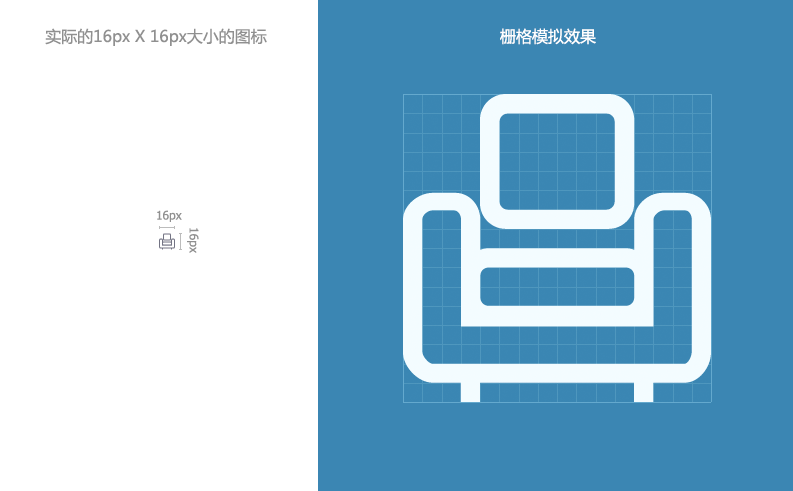
那有同学就要问了,通过这样的栅格能达到什么样的优化效果呢?首先我们来了解一下文字的渲染策略,看组图:
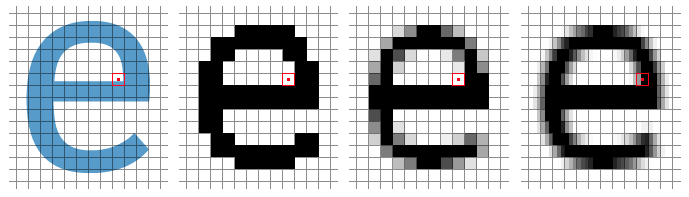
(从左到右依次)理想的渲染状态、黑白渲染、灰度渲染、次像素渲染
上图左侧第一张是我们认为一种比较理想的渲染效果,但是通过刚才我们介绍栅格我们可以了解到这种状态是不可能的,因为第一代黑白渲染和第二代灰度渲染是不可能做到显示半格像素或一个像素中显示弧度的。
黑白渲染和灰度渲染在渲染图形遇到半格像素或则弧度的时候,他们会有各自不同的处理方式;举个例子:
如上图红点处像素,我们理解他是有弧度的,且不占满一个像素;各个渲染方式的处理办法如下:
黑白渲染
黑白渲染相对来说比较粗暴,直接通过四舍五入的形式把这里要描绘的图形不显示了;(黑白渲染的形式主要应用于打印机渲染,但是打印机本身的精度非常高,所以打印出来的图形还是很细腻的)
灰度渲染
灰度渲染显得就智能一些了,他通过灰度降级的方式来表达,如果占不到一个像素那就根据他占的面积来降低这个像素的灰度;占的面积越小灰度就越低;
次像素渲染
次像素渲染是第三代渲染方式,相对来说比较高级,他从从左至右将一个像素分成三份;用不同的色彩值来显示图形,这样图形看起来就更加细腻;
通过了解刚才三种渲染模式对不满一个像素的处理方式,我们就会发现,当我们绘制图标的时候,如果没有把控好图标边缘线在真实场景下渲染的情况,就会被系统进行降级渲染。所以我们更希望能饱满完整的显示一个像素。我们来看一组效果:
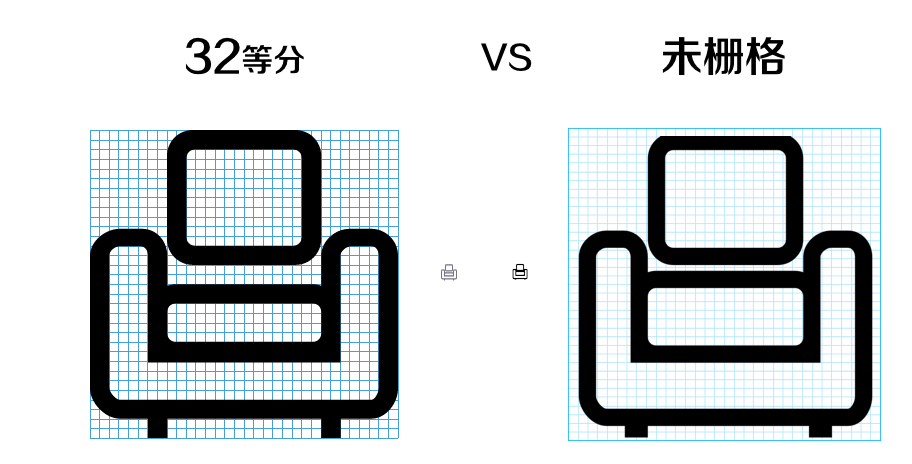
从上组图中我们可以看出左侧图形的边都刚好落在完成的像素中,未出现不足一个像素的现象(圆角除外),右侧则未考虑像素栅格的问题;图标在16X16像素大小的应用中很明显感觉到左侧的小图标比右侧的小图标要清晰很多;这是因为右侧的图标的边本来是需要2个像素显示的,但是却落在了3个像素上,渲染的时候出现了一个像素是未降级灰度显示,其他两个像素进行了不同级别的灰度降级。这样我们就会觉得右侧的小图标有点模糊且变粗了。所以在制作图标的时候我们需要引入栅格,去模拟像素点,然后避免图标的线或边不要出现落在半个像素上的情况;
了解到了栅格对于图标优化的重要性,那怎么制作一个能模拟真实像素环境下的栅格呢?
首先我们得了解一下基准框;基准框的作用是为字体矢量图标提供一个大小参考,如:在16px像素大小的一个逗号“,”和一个文字“图”的大小和所处的位子是不一样的,这就是因为他们都是在同一套基准框中绘制的图形,才得到相对大小的概念,不然大家同时矢量图标,怎么区别大小呢?
每套字体都有自己不同的基准框,要根据实际设计需要设定,没有严格规定;阿里巴巴矢量图标库在制定基准框的时候考虑到图标展现的标准尺寸:16X16、32X32、64X64、128X128;特设置了一个可以整除他们的尺寸:1024X1024(大家可以通过下载我们制作好的“图标制作模板”获得已经设置好基准框的模板)
根据实际应用的像素大小选择栅格;
如:你要制作一套16X16像素大小的字体图标应用于网站或app,那么我们建议您在16X16的栅格中绘制,那么16像素2的n倍都能应用,这样图标的边框就不会落在半个像素上,避免出现虚边、加粗等现象。(在retina屏下不用担心图标的虚边问题,由于显示精度非常高,图标表现得非常细腻。)
那如果要制作一个非标尺寸的图标,如:18X18大小的图标怎么办呢?
我们可以通过在AI中修改栅格来实现模拟,如下图:
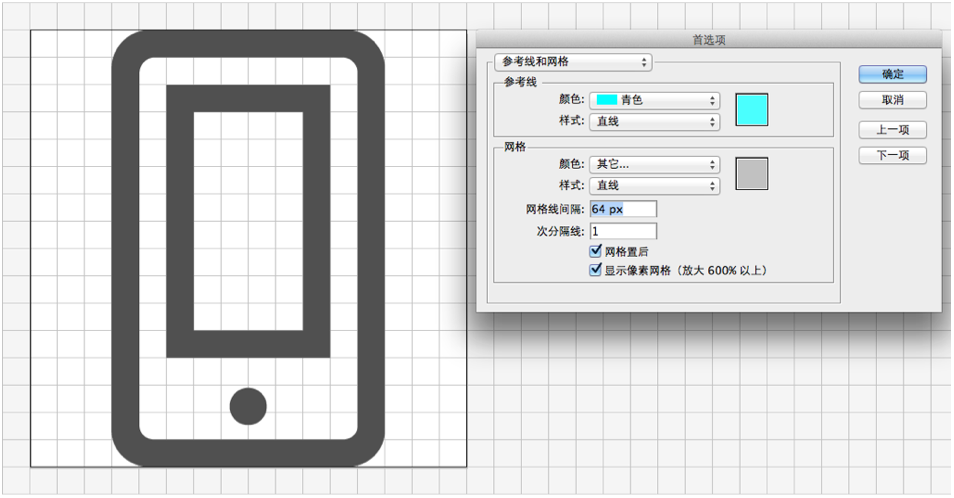
在AI设置中调出参考线和网格设置设置项,然后拿出你的计算机:1024/X=?把算出来的值尽可能精确的填入网格线间隔这项中,这样你可以模拟在实际应用大小场景中要显示的图形像素点了。
三、实例操作
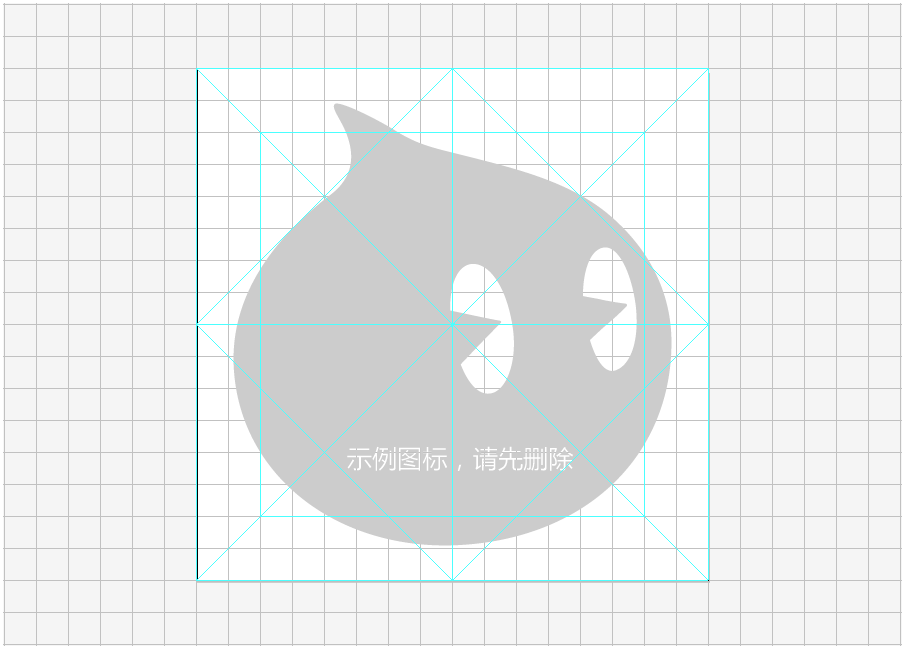
2、在AI中删除模板的示例图,根据栅格绘制图形;
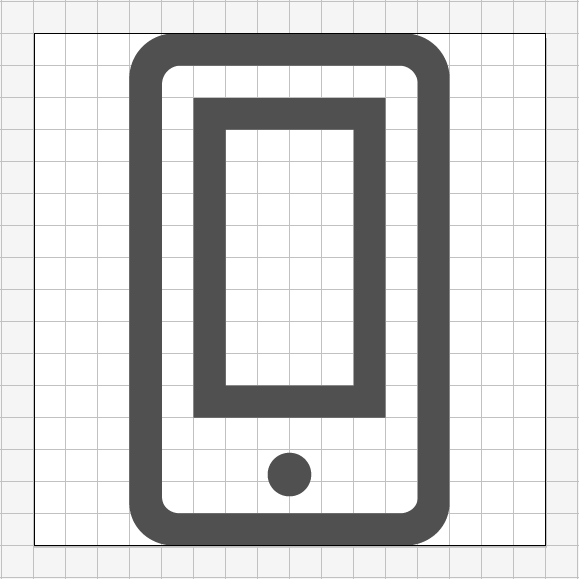
5、完成上传,这样就获得了一个矢量的字体图标